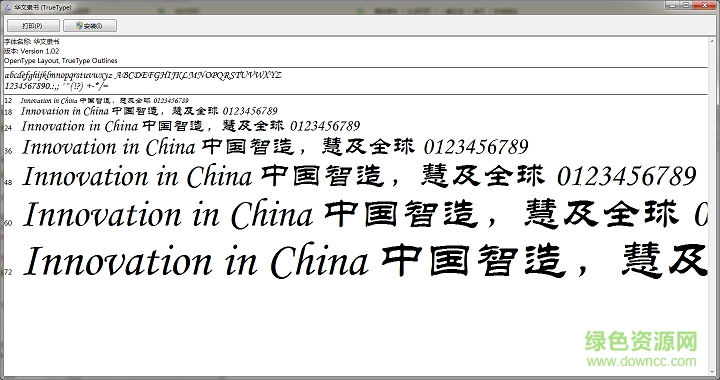
stliti字体
stliti是什么字体?stliti字体就是华文隶书字体,这款字体可以说是目前电脑上应用最广泛的隶书字体了,笔画舒展,弧度优美,韵味内含,美观又大气!
stliti字体特点
华文隶书体非常美观,是一种美丽的字体,起源于隶书体。华文隶书体被许多网站应用为logo上文字的字体,也被许多广告商用做重点字体。
stliti regular
华文隶书隶书体的差异
华文隶书虽然是由隶书演变而来,但是与隶书却存在明显的差异。隶书较扁、较圆滑,而华文隶书给人的感觉是较为方正,又充满艺术的感觉,并非普通的草体、楷体所能比的。